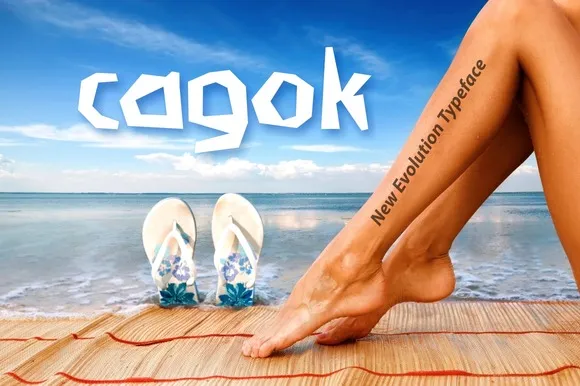
A Cagok Font é uma fonte display que traz a essência vibrante do movimento typográfico conhecido como Cagok Action. Esta fonte estilosa e poderosa transmite claramente ideias, com um tom áspero mas ainda assim expressivo. Ideal tanto para logotipos quanto para posters, também é perfeita para maquetes ou qualquer outro uso que exija uma escrita atraente e imediata. A Cagok Font está disponível gratuitamente para quem desejar adicionar ao seu projeto um toque de movimento e originalidade.